24 font chữ tham khảo cho thiết kế website - Phần 2
Trong bài trước, Ngôi Sao Số đã giới thiệu phần 1 của "24 font chữ tham khảo cho thiết kế website". Hôm nay, Ngôi Sao Số xin giới thiệu tiếp với các bạn phần 2.
13. Amatic - Download font
Một thiết kế mới mẻ với font chữ hẹp và đậm của nhà thiết kế Vernon Adams. Font chữ này gồm cả chữ hoa và chữ thường.
14. Journal - Download font
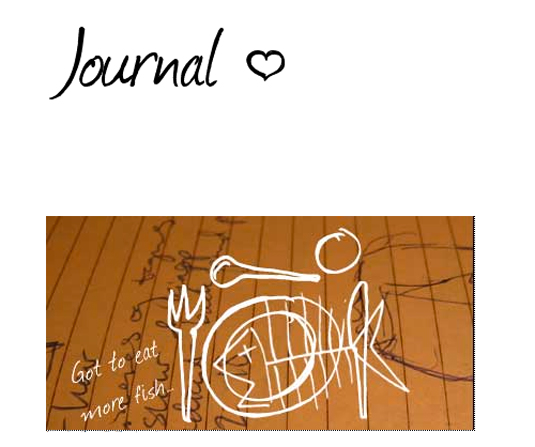
Được thiết kế bởi Hans Gerhard Meier
15. Mari & David - Download font
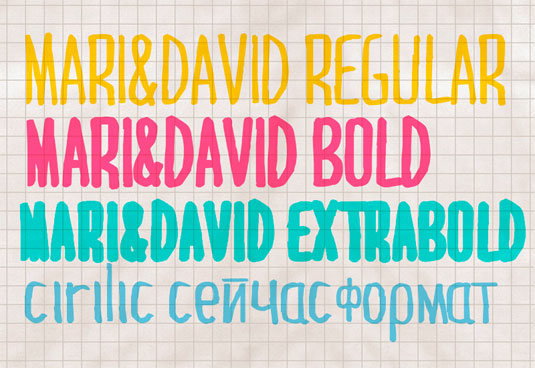
Được thiết kế bởi Rodrigo German
16. DHD Cool: Regular - Download font
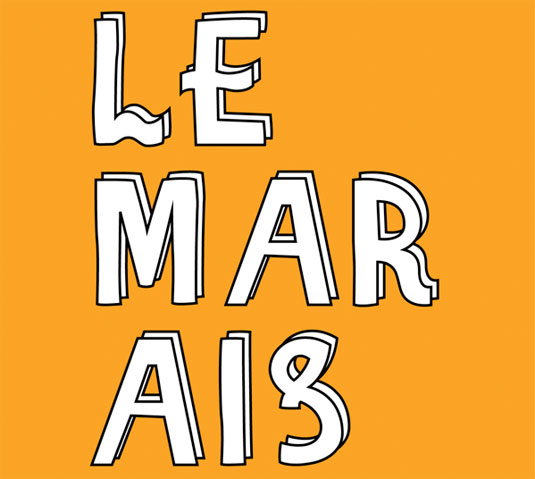
Được thiết kế bởi Konrad Bednarksi
17. Sumitra - Download font
Được thiết kế bởi Ananda Maharjan (người Nepal)
18. LSTK Clarendon - Download font
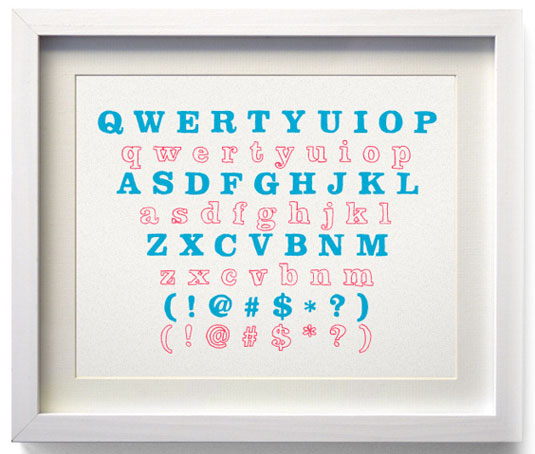
Thiết kế của Studio Elastik
19. Mawn's Handwriting - Download font
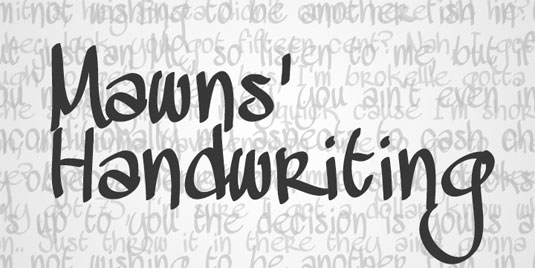
Thiết kế của Måns Grebäck
20. Bispo - Download font
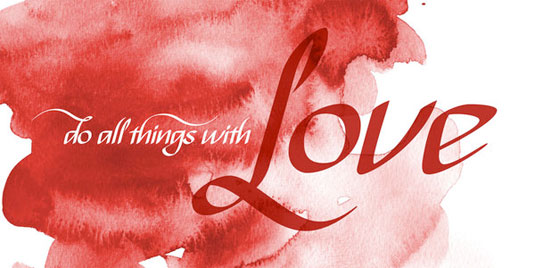
Thiết kế của Jackson Alves
21. Scribulous Scrawlin' - Download font
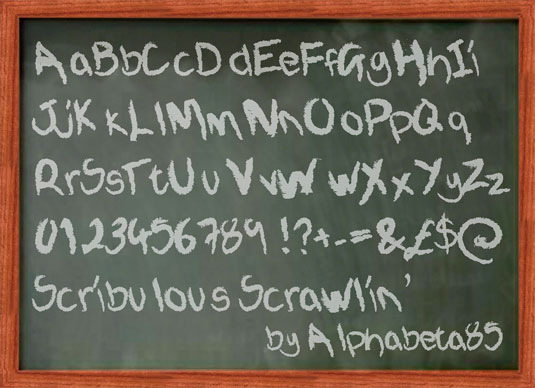
Thiết kế của Alphabeta85
22. Linny - Download font
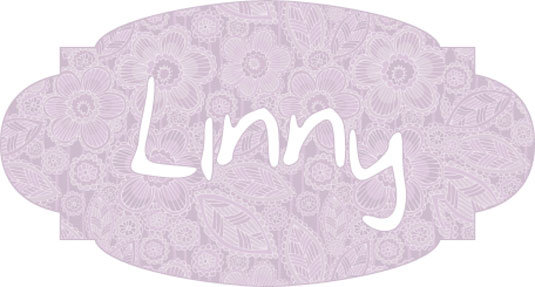
Thiết kế của Maya
23. Fatstack - Download font
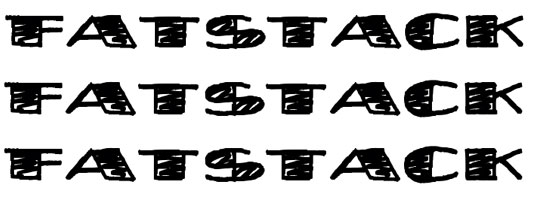
Thiết kế của Blambot Comic Fonts and Lettering
24. Soft Sugar- Download font